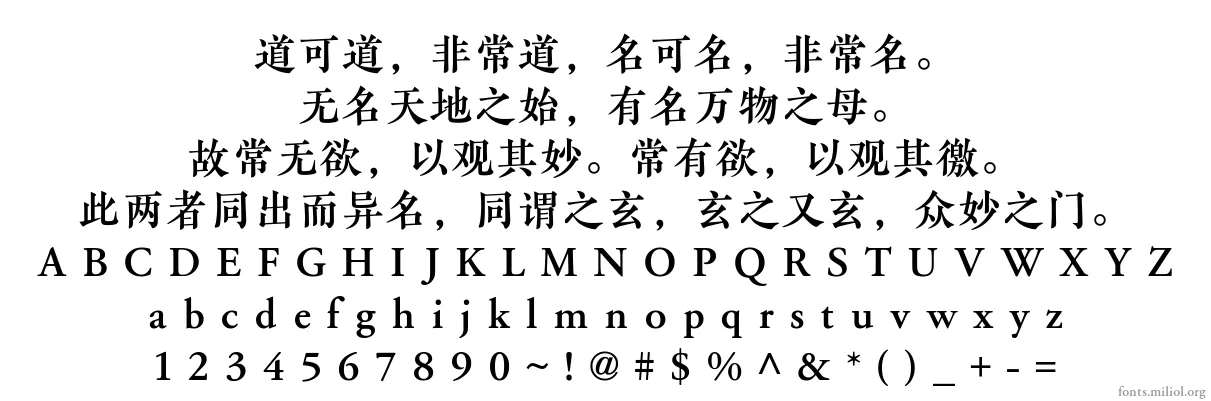
**《FZJinL-B_GBJF 字体简介与应用场景》**
FZJinL-B_GBJF(标准编号FZJINB_GBJF--GB1-0)是一款符合国家标准的中文字体,设计风格兼具传统印刷体的规范性与现代审美的简洁感。其笔画结构匀称,横平竖直的笔触适合正式文档排版,尤其在印刷品、出版物或企业宣传材料中能体现专业性与权威性。
该字体属于方正字库系列,支持GB2312字符集,覆盖常用汉字及符号,适用于标题、正文等多种场景。其清晰的辨识度使其在屏幕显示时也能保持良好效果,适合用于网页设计、PPT演示或电子书制作。此外,FZJinL-B_GBJF的标准化设计确保了与其他办公软件的兼容性,方便用户跨平台使用。